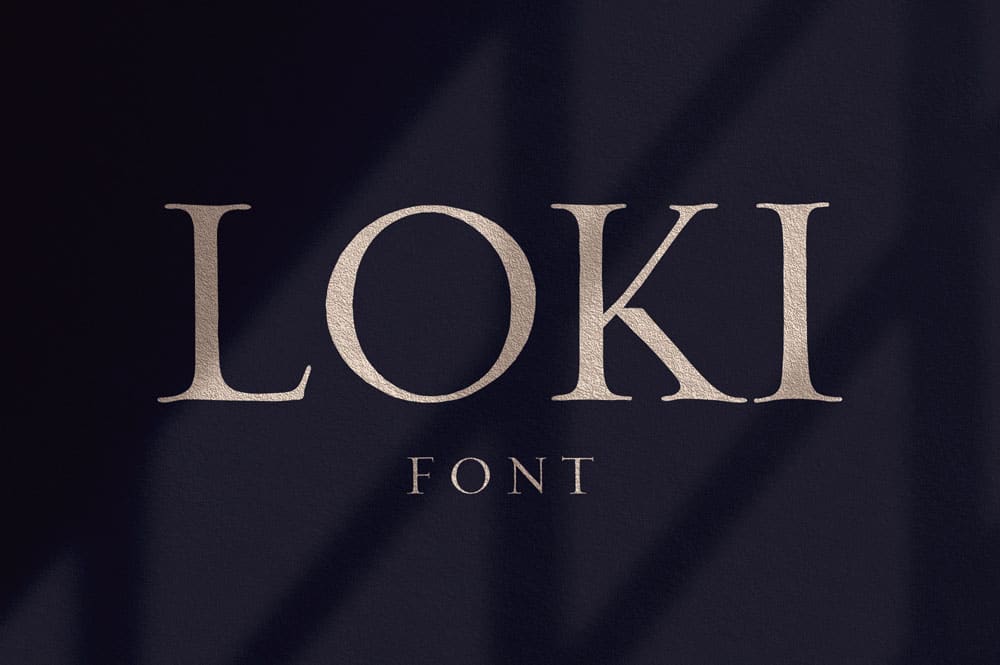
Loki ist ein handgeschriebenes Sans Serif Brush Script. Es ist perfekt für große Titel.
Der Font verfügt über starke Glyphen mit einzigartigen Schnörkeln. Der Name Loki wurde von einem der alten Nordischen Götter inspiriert – Loki – der hübsche und hinterlistige Sohn eines Riesen. Er ist der vielseitigste aller Götter.
Die Schrift wurde von Krisjanis Mezulis und Ieva Mezule erstellt. Sie ist kostenlos für persönliche und kommerzielle Projekte.